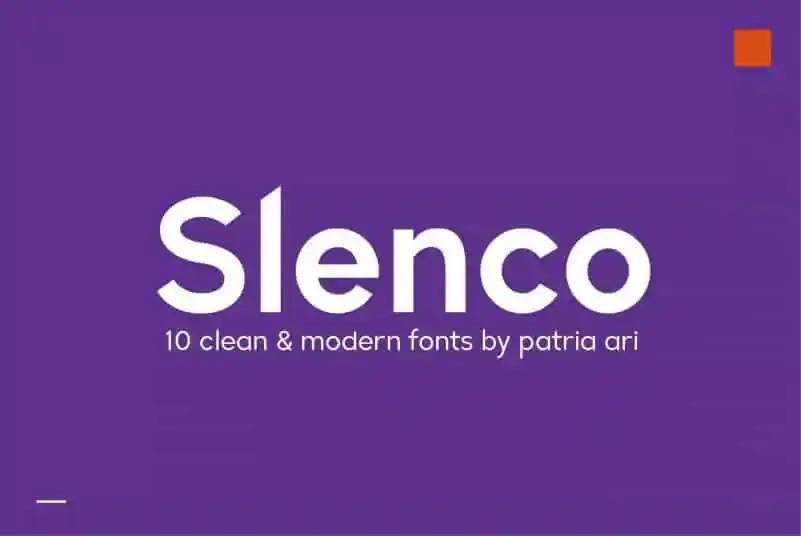
Slenco Sans Serif Font
Introduzimos a Slenco Sans Serif Font, uma família moderna de tipo sans serif criada pela Patria Ari Typestudio. Esta elegante família de fontes apresenta variedade no formato do traço e tamanho, desde Thin até Black, permitindo-lhe explorar infinitas possibilidades criativas. Agradável para headlines em qualquer tamanho, ideal para desenho editorial, design de marca, embalagens, web ou televisão, a Slenco é uma fonte versátil que atende a uma ampla gama de usos gráficos. Não perca esta oportunidade de dar um toque moderno e sofisticado a seus projetos.